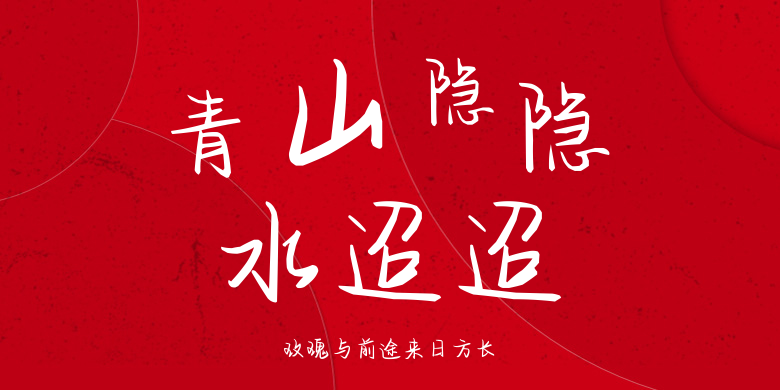
玫瑰与前途来日方长
玫瑰与前途来日方长,这款字体结构工整、笔画清晰,兼顾美观与易读性,适用于标题、正文、海报、包装、LOGO 等多种场景。字形优雅稳定,风格百搭耐看,适配日常排版与创意设计,让文字呈现更舒适、更具质感。玫瑰与前途来日方长一笔一画,皆是细节,以均衡的比例、流畅的线条打造舒适视觉体验,字形端正大气,风格简约现代。无论是商业设计、品牌宣传还是日常排版,都能轻松驾驭,让文字更有格调与力量。玫瑰与前途来日方长字体下载。